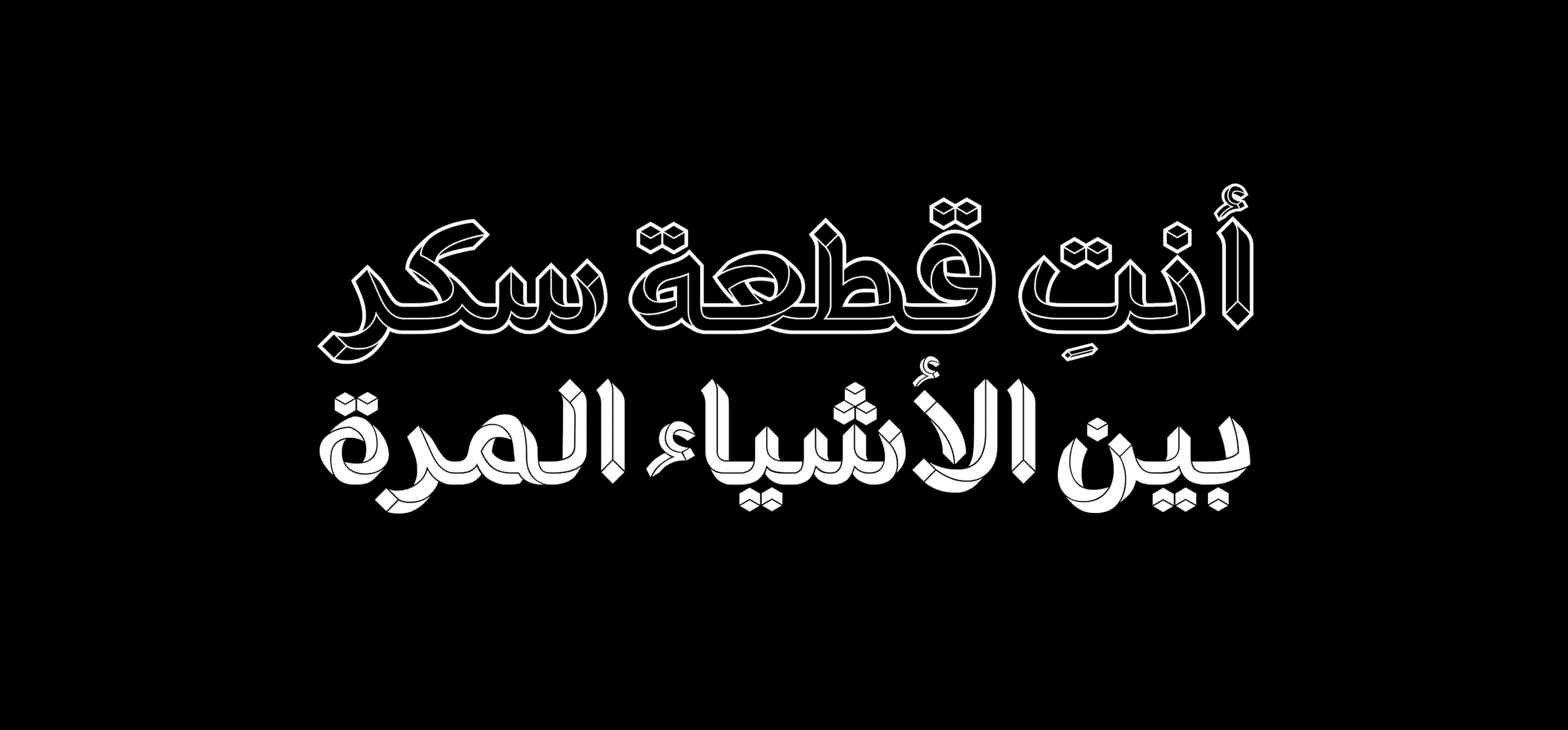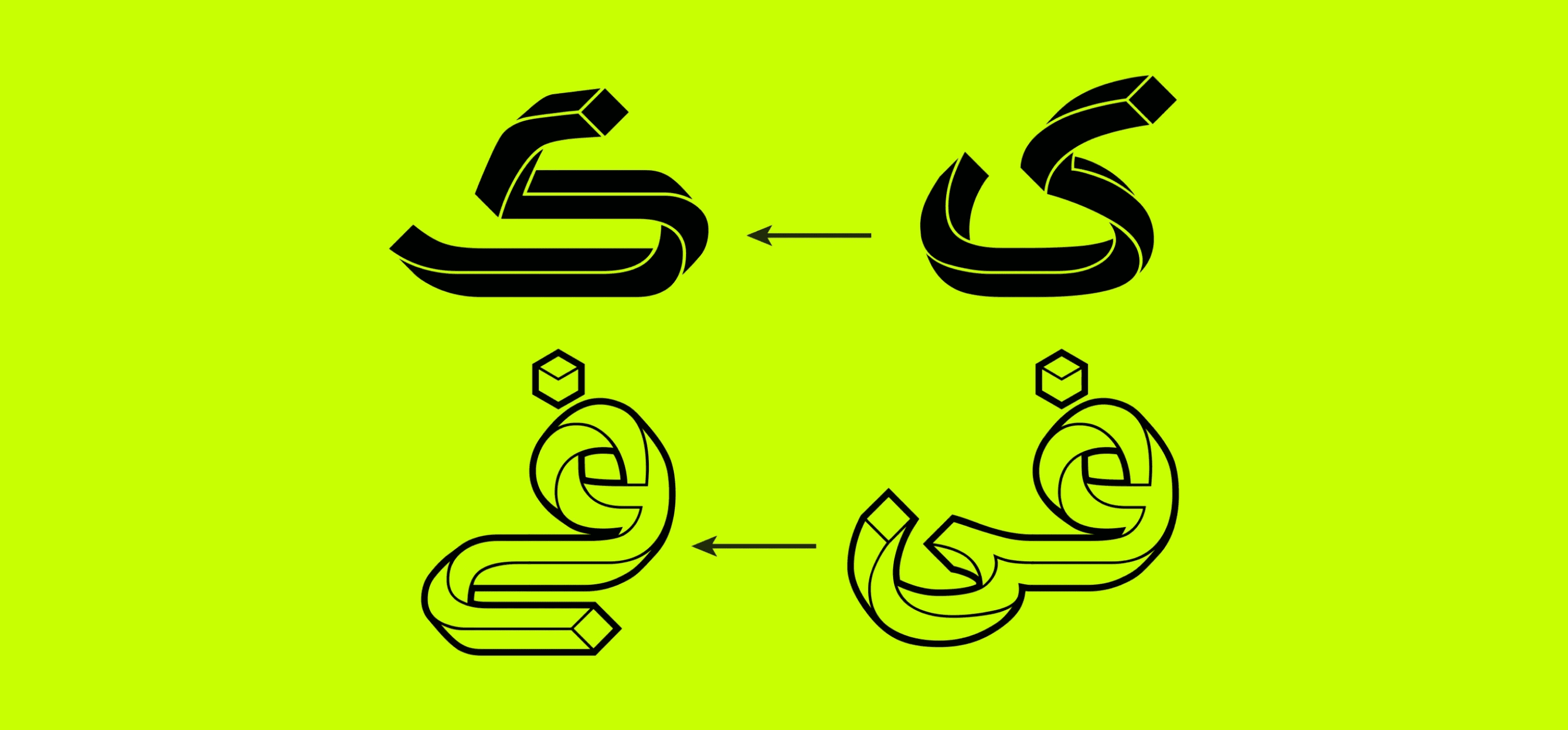
بدأت فكرة إنشاء خط Paradox في عام 2014 نتيجة اهتمامي الشخصي بأعمال موريس إيشر. بدأت تصميمه من خلال التجربة والخطأ، وخلال هذه العملية، اكتشفت بعض الخطوط اللاتينية التي سلكت نفس النهج.
لكن حروف اللغة العربية كانت أكثر تعقيدًا من نظيرتها اللاتينية، ولم تكن أنماط الكتابة اللاتينية قابلة للتطبيق، لذا كان عليّ أن أقضي وقتًا طويلًا في حل هذه التحديات.
في عام 2019، بدأت أركز بشكل أكثر جدية على تصميم الخط، وبنهاية ذلك العام كان التصميم والتنفيذ البرمجي شبه مكتملين. وفي عام 2022، وبدعم دقيق وفعّال من صديقي العزيز أمين عابدي (في جانب البرمجة)، أصبح خط Paradox جاهزًا للإصدار النهائي.